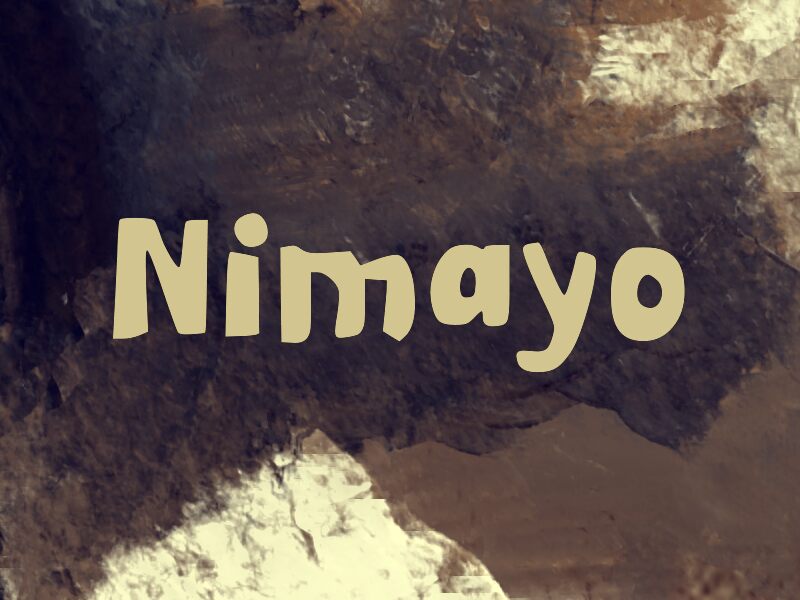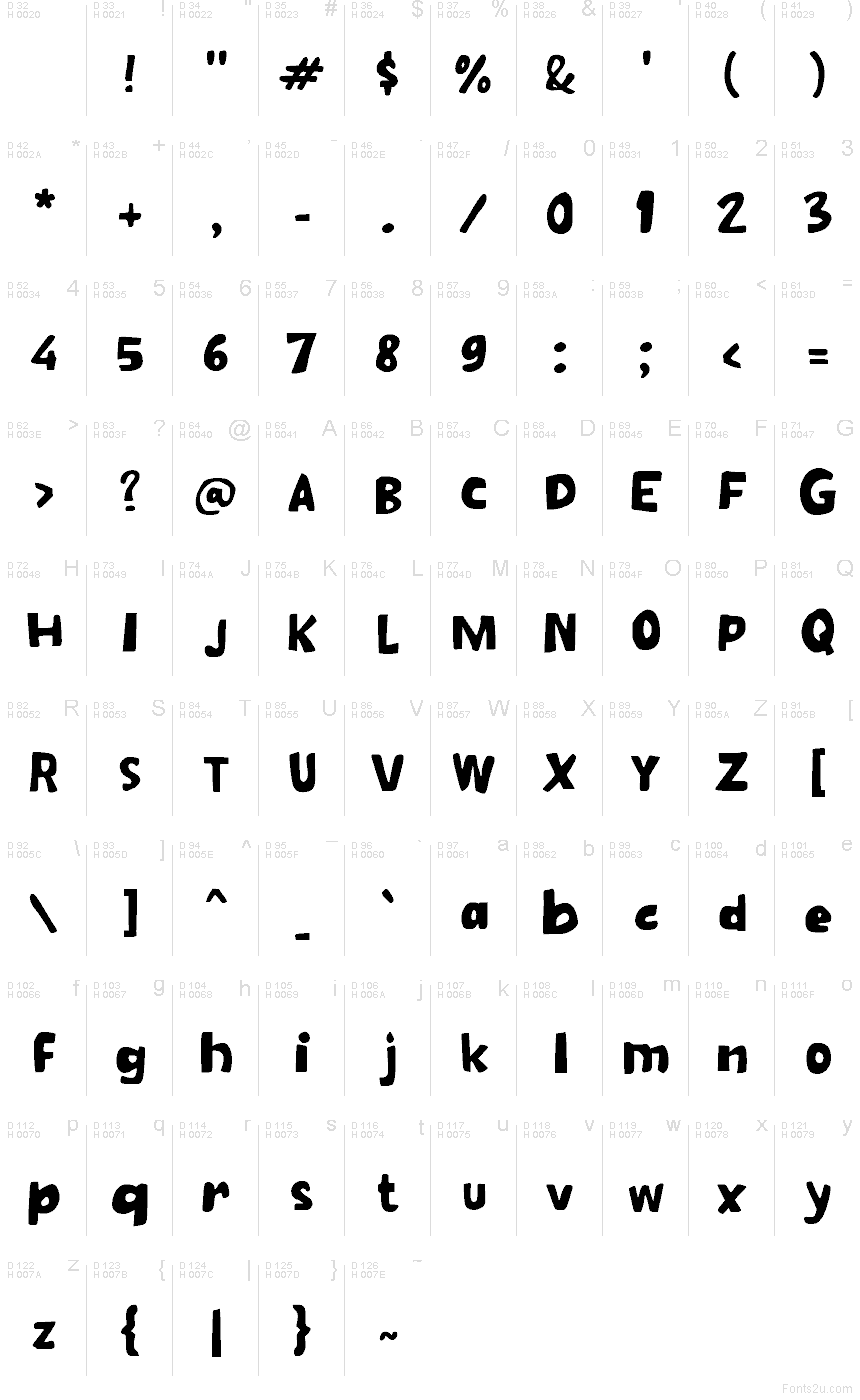
Nimayo od Wep je bezplatné, zkreslené displejové písmo s uvolněným rytmem připomínajícím papírové vystřihovánky a hravým dojmem ruční práce. Písmena kolísají mezi baculatými a sevřenými tvary, se zaoblenými hranami, nepravidelnými spoji a mírně pokřiveným odskokem, díky čemuž nápis působí živě, nikoliv strojeně.
Hodí se na titulky plakátů, vizuály indie hudby, obálky zinů, obaly a hlavičky na sociálních sítích, kde bezplatné písmo může vnést zvláštně přátelský tón bez dojmu přílišné uhlazenosti. Použijte ho pro krátké brandingové texty, titulní karty nebo velké citace, zejména pokud chcete, aby písmena působila měkce, neotřele a trochu jako od ruky.
Nimayo